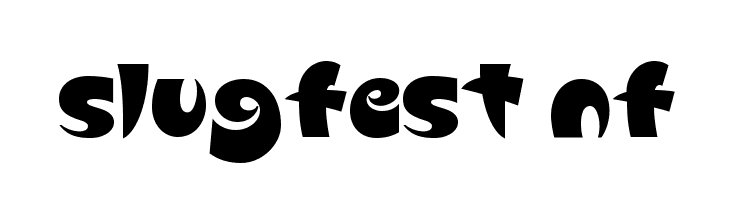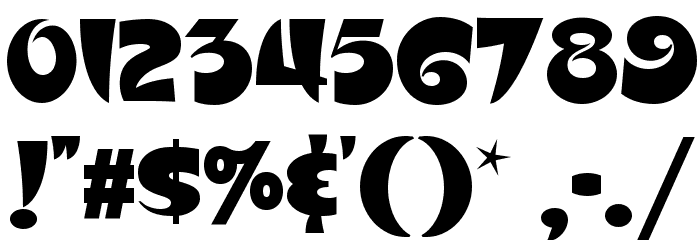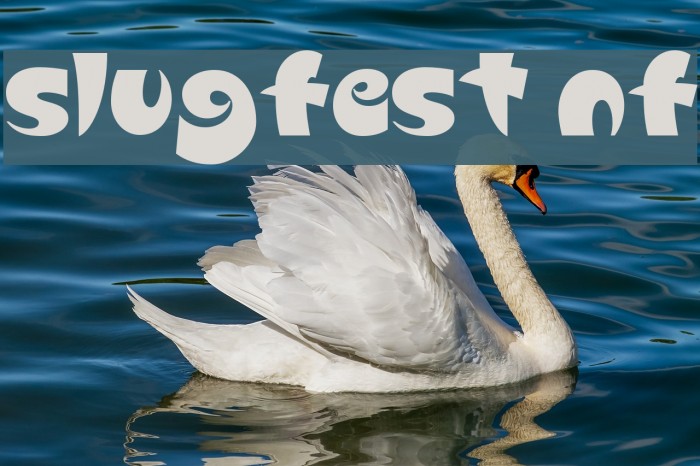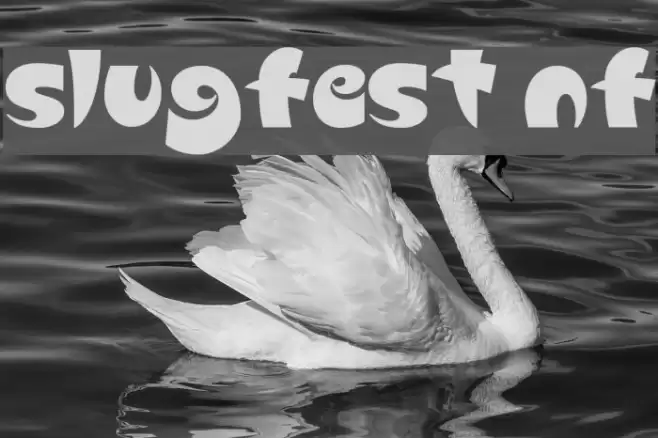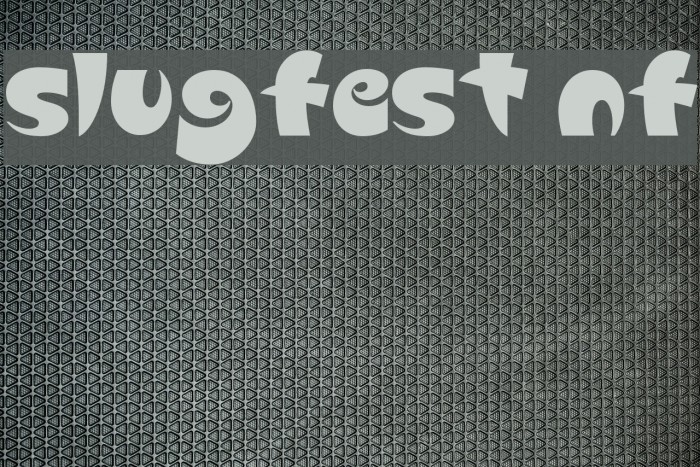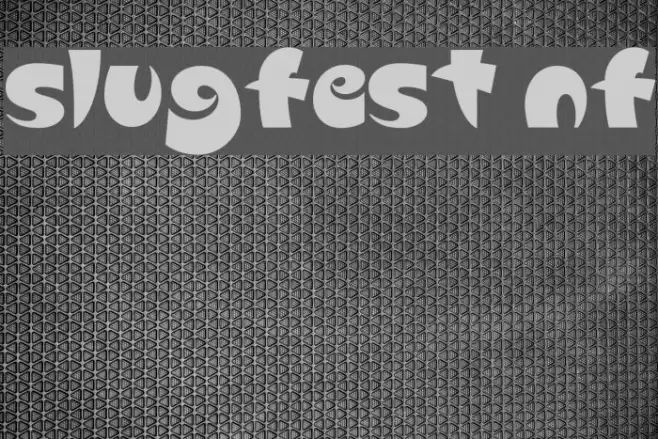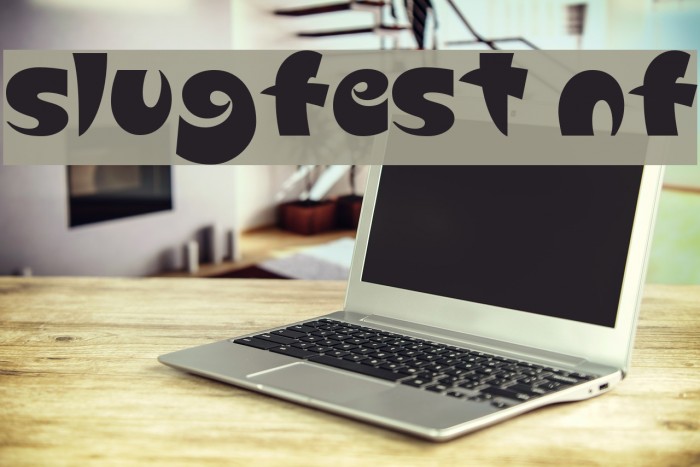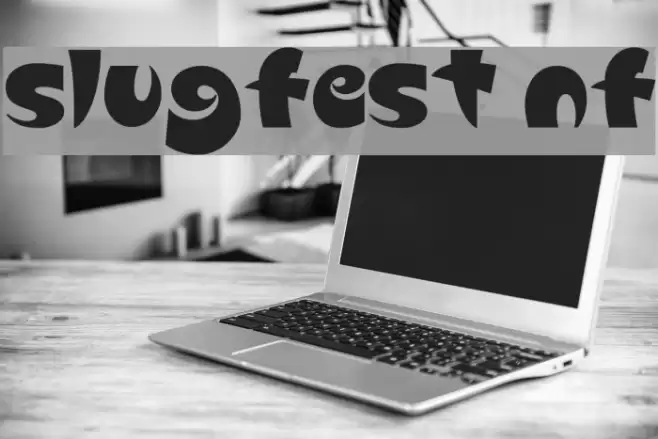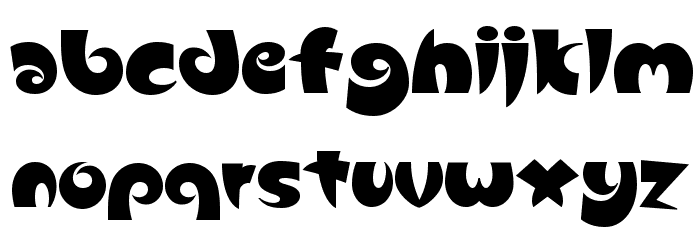
Slugfest NF Font
| Stile generale | Playful, Whimsical |
| Progetti proposti | Ideal for children's books, playful branding, party invitations, and creative posters. |